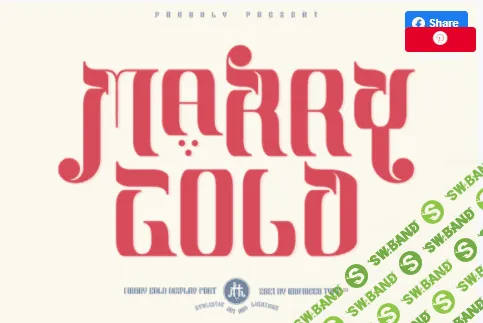
Название: Marry Gold Font (2021)
Marry Gold - невероятно крутой и интересно оформленный дисплейный шрифт. Добавьте этот модный шрифт в свою библиотеку и исследуйте его безграничные возможности. Этот шрифт имеет кодировку PUA, что означает, что вы можете легко получить доступ ко всем глифам и росчеркам!